Halloween không chỉ là dịp lễ để hóa trang và trang trí không gian, mà còn là cơ hội lý tưởng để thể hiện sự sáng tạo qua các thiết kế độc đáo. Với tinh thần lễ hội đầy bí ẩn và ma mị, việc chọn font chữ phù hợp có thể giúp bạn nâng tầm các dự án thiết kế của mình. Trong bài viết này, chúng tôi sẽ tổng hợp những font Việt hóa ấn tượng nhất dành riêng cho ngày Halloween, mang đến cho bạn những lựa chọn hoàn hảo để tạo nên những thiết kế đầy cá tính và đậm chất lễ hội.
Mystery Quest là một font chữ hiển thị độc đáo, mang đậm tính chất kỳ bí và phiêu lưu. Với các nét vẽ uốn lượn, font này gợi lên cảm giác hoài cổ, ma mị như bước vào một thế giới cổ tích hay những cuộc phiêu lưu đầy bí ẩn, không khí của lễ hội bí ngô.
Font chữ “Zombie Zone” là một kiểu chữ độc đáo, lấy cảm hứng từ phong cách kinh dị, đặc biệt phù hợp với các chủ đề zombie, ma quái và Halloween. Chữ được thiết kế với những nét dày, uốn cong, mang cảm giác nặng nề và kỳ bí. Phần góc của các chữ cái được làm tròn, tạo cảm giác mềm mại, nhưng vẫn giữ được nét mạnh mẽ. Font có màu vàng nhạt nổi bật trên nền đỏ tối và rừng cây u ám, tạo nên sự tương phản mạnh mẽ, giúp chữ dễ đọc và thu hút sự chú ý. Sự phối hợp màu sắc và kiểu chữ độc đáo này làm tăng tính thẩm mỹ cho các thiết kế liên quan đến zombie và bối cảnh kinh dị. Font chữ này phù hợp sử dụng cho các bìa game, phim kinh dị, áp phích quảng cáo hoặc các sản phẩm sáng tạo khác liên quan đến đề tài rùng rợn và ngộ nghĩnh.
Rubik Wet Paint Việt hóa là một font chữ hiển thị (display font) mang phong cách ma mị – Halloween cực kỳ ấn tượng. Với hiệu ứng sơn ướt nhỏ giọt, kiểu chữ này tạo nên cảm giác rùng rợn, huyền bí, rất phù hợp để sử dụng trong các thiết kế mùa lễ hội Halloween, poster phim kinh dị, tiêu đề game hoặc ấn phẩm truyền thông spooky.
Jolly Lodger là font chữ hoàn hảo cho các thiết kế Halloween nhờ vào phong cách kỳ quái và vui nhộn. Với các đường nét gồ ghề và dáng vẻ độc đáo, font này tạo ra cảm giác vừa rùng rợn vừa vui tươi, gợi lên hình ảnh những biển hiệu ma quái hay những câu chuyện kinh dị nhưng đầy màu sắc. Đây là lựa chọn lý tưởng cho các tiêu đề Halloween, poster sự kiện, hoặc thiệp mời với không khí kỳ bí nhưng không kém phần thú vị và sáng tạo.
Font DVN - Reloading có phong cách cổ điển với các nét cong, nhọn và dày, tạo cảm giác bí ẩn và hoài cổ. Thiết kế chi tiết, thanh lịch này phù hợp với chủ đề Halloween, khi kết hợp với các yếu tố trang trí tối màu và ma mị. Nó tạo ra không khí u ám, phù hợp cho các dự án thiết kế liên quan đến lễ hội.
DVN DEMON Việt hóa là font chữ mang đậm dấu ấn của bóng tối và sức mạnh với những đường cắt sắc lạnh và táo bạo. Phù hợp với các dự án thiết kế mang phong cách kinh dị, bí ẩn, và u ám, font này tạo nên cảm giác mạnh mẽ, đầy ám ảnh.
You Murder BB là một font chữ viết tay phong cách kinh dị, phù hợp cho các dự án về phim ảnh và logo cần yếu tố đáng sợ, kịch tính và bí ẩn. Font chữ này mang đến cảm giác thủ công, như thể được viết bằng tay bởi một nhân vật phản diện, với các đường nét thô ráp, không đều và đầy tính ngẫu nhiên. Những đường nét sắc nhọn, các ký tự biến dạng tạo nên một không khí đe dọa và hồi hộp, phù hợp cho các dự án phim kinh dị, logo các thương hiệu liên quan đến thể loại kinh dị hoặc những sản phẩm cần tạo cảm giác kỳ bí, rùng rợn.
DVN Dark là một font chữ mang phong cách mạnh mẽ và đầy bí ẩn, lý tưởng cho các dự án thiết kế đậm chất fantasy và dark-themed. Nét chữ dày, góc cạnh và cứng cáp tạo cảm giác uy nghi và quyền lực, khiến font này trở thành lựa chọn hoàn hảo cho tiêu đề, poster, và logo trong các dự án liên quan đến game, truyện tranh, hoặc phim ảnh thể loại kỳ ảo, kinh dị.
DVN - Wicked là một font chữ đầy phong cách, lấy cảm hứng từ không khí ma mị của Halloween. Với những đường cong mạnh mẽ và chi tiết uốn lượn tinh tế, DVN - Wicked mang lại cảm giác rùng rợn nhưng đầy quyến rũ. Các ký tự được thiết kế độc đáo, tạo sự cân đối giữa sự cổ điển và hiện đại, phù hợp cho các dự án sáng tạo, áp phích lễ hội, hoặc thương hiệu mang chủ đề kỳ bí.
Midnight Minutes là một phông chữ hiển thị theo phong cách gothic với cảm giác kỳ ảo, rùng rợn và huyền bí với nhiều yếu tố xoăn và sắc nét lấy cảm hứng từ phim kinh dị và kỳ ảo! Midnight Minutes mang đến cho bạn bầu không khí đáng sợ và độc ác cho các dự án thiết kế của bạn. Phù hợp với tiêu đề sách/tiểu thuyết hoặc phim, logo & thương hiệu, bài đăng trên phương tiện truyền thông xã hội, quảng cáo & thiết kế sản phẩm, v.v.
DVN Mystery Quest Việt hóa
Mystery Quest là một font chữ hiển thị độc đáo, mang đậm tính chất kỳ bí và phiêu lưu. Với các nét vẽ uốn lượn, font này gợi lên cảm giác hoài cổ, ma mị như bước vào một thế giới cổ tích hay những cuộc phiêu lưu đầy bí ẩn, không khí của lễ hội bí ngô.
DVN Zombie Zone Việt hóa
Font chữ “Zombie Zone” là một kiểu chữ độc đáo, lấy cảm hứng từ phong cách kinh dị, đặc biệt phù hợp với các chủ đề zombie, ma quái và Halloween. Chữ được thiết kế với những nét dày, uốn cong, mang cảm giác nặng nề và kỳ bí. Phần góc của các chữ cái được làm tròn, tạo cảm giác mềm mại, nhưng vẫn giữ được nét mạnh mẽ. Font có màu vàng nhạt nổi bật trên nền đỏ tối và rừng cây u ám, tạo nên sự tương phản mạnh mẽ, giúp chữ dễ đọc và thu hút sự chú ý. Sự phối hợp màu sắc và kiểu chữ độc đáo này làm tăng tính thẩm mỹ cho các thiết kế liên quan đến zombie và bối cảnh kinh dị. Font chữ này phù hợp sử dụng cho các bìa game, phim kinh dị, áp phích quảng cáo hoặc các sản phẩm sáng tạo khác liên quan đến đề tài rùng rợn và ngộ nghĩnh.
DVN Rubik Wet Paint Việt hóa
Rubik Wet Paint Việt hóa là một font chữ hiển thị (display font) mang phong cách ma mị – Halloween cực kỳ ấn tượng. Với hiệu ứng sơn ướt nhỏ giọt, kiểu chữ này tạo nên cảm giác rùng rợn, huyền bí, rất phù hợp để sử dụng trong các thiết kế mùa lễ hội Halloween, poster phim kinh dị, tiêu đề game hoặc ấn phẩm truyền thông spooky.
DVN Jolly Lodger Việt hóa
Jolly Lodger là font chữ hoàn hảo cho các thiết kế Halloween nhờ vào phong cách kỳ quái và vui nhộn. Với các đường nét gồ ghề và dáng vẻ độc đáo, font này tạo ra cảm giác vừa rùng rợn vừa vui tươi, gợi lên hình ảnh những biển hiệu ma quái hay những câu chuyện kinh dị nhưng đầy màu sắc. Đây là lựa chọn lý tưởng cho các tiêu đề Halloween, poster sự kiện, hoặc thiệp mời với không khí kỳ bí nhưng không kém phần thú vị và sáng tạo.
DVN Reloading Việt hóa
Font DVN - Reloading có phong cách cổ điển với các nét cong, nhọn và dày, tạo cảm giác bí ẩn và hoài cổ. Thiết kế chi tiết, thanh lịch này phù hợp với chủ đề Halloween, khi kết hợp với các yếu tố trang trí tối màu và ma mị. Nó tạo ra không khí u ám, phù hợp cho các dự án thiết kế liên quan đến lễ hội.
DVN DEMON Việt hóa
DVN DEMON Việt hóa là font chữ mang đậm dấu ấn của bóng tối và sức mạnh với những đường cắt sắc lạnh và táo bạo. Phù hợp với các dự án thiết kế mang phong cách kinh dị, bí ẩn, và u ám, font này tạo nên cảm giác mạnh mẽ, đầy ám ảnh.
SVN You Murder BB Việt hóa
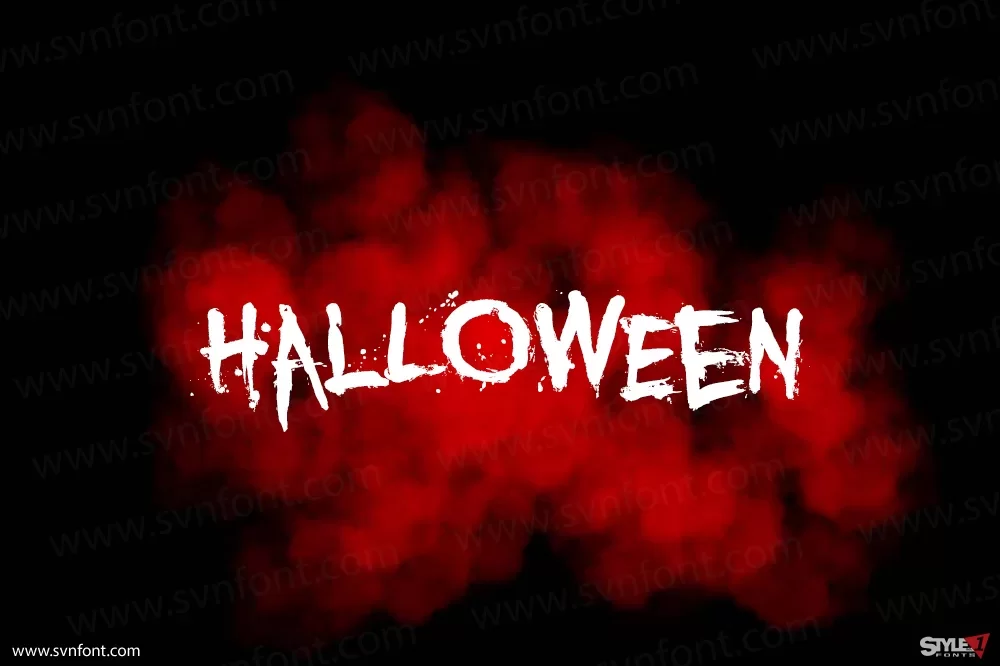
You Murder BB là một font chữ viết tay phong cách kinh dị, phù hợp cho các dự án về phim ảnh và logo cần yếu tố đáng sợ, kịch tính và bí ẩn. Font chữ này mang đến cảm giác thủ công, như thể được viết bằng tay bởi một nhân vật phản diện, với các đường nét thô ráp, không đều và đầy tính ngẫu nhiên. Những đường nét sắc nhọn, các ký tự biến dạng tạo nên một không khí đe dọa và hồi hộp, phù hợp cho các dự án phim kinh dị, logo các thương hiệu liên quan đến thể loại kinh dị hoặc những sản phẩm cần tạo cảm giác kỳ bí, rùng rợn.
DVN DARK
DVN Dark là một font chữ mang phong cách mạnh mẽ và đầy bí ẩn, lý tưởng cho các dự án thiết kế đậm chất fantasy và dark-themed. Nét chữ dày, góc cạnh và cứng cáp tạo cảm giác uy nghi và quyền lực, khiến font này trở thành lựa chọn hoàn hảo cho tiêu đề, poster, và logo trong các dự án liên quan đến game, truyện tranh, hoặc phim ảnh thể loại kỳ ảo, kinh dị.
DVN Dragon Slayer Việt hóa
DVN Wicked Việt hóa
DVN - Wicked là một font chữ đầy phong cách, lấy cảm hứng từ không khí ma mị của Halloween. Với những đường cong mạnh mẽ và chi tiết uốn lượn tinh tế, DVN - Wicked mang lại cảm giác rùng rợn nhưng đầy quyến rũ. Các ký tự được thiết kế độc đáo, tạo sự cân đối giữa sự cổ điển và hiện đại, phù hợp cho các dự án sáng tạo, áp phích lễ hội, hoặc thương hiệu mang chủ đề kỳ bí.
SVN-Midnight Minutes
Midnight Minutes là một phông chữ hiển thị theo phong cách gothic với cảm giác kỳ ảo, rùng rợn và huyền bí với nhiều yếu tố xoăn và sắc nét lấy cảm hứng từ phim kinh dị và kỳ ảo! Midnight Minutes mang đến cho bạn bầu không khí đáng sợ và độc ác cho các dự án thiết kế của bạn. Phù hợp với tiêu đề sách/tiểu thuyết hoặc phim, logo & thương hiệu, bài đăng trên phương tiện truyền thông xã hội, quảng cáo & thiết kế sản phẩm, v.v.